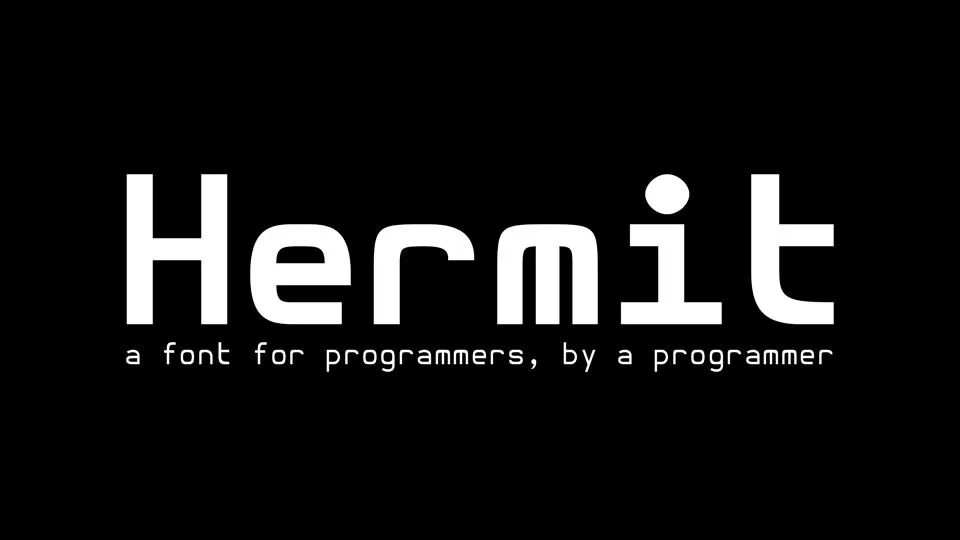
A fonte Hermit é uma família de tipo geometricamente simples desenvolvida para ser clara, prática e extremamente legível. Suas linhas são diretas e retas, criando um visual minimalista que se destaca perfeitamente em ambientes digitais modernos. Combinada com seu foco nas práticas do desenvolvimento de software, a Hermit é uma escolha perfeita para designers gráficos, especialmente aqueles dedicados ao design web ou programação. A atenção aos detalhes na criação da fonte garante que cada letra seja calculada e planejada segundo preceitos bem definidos, resultando em um conjunto de caracteres consistente e regular. Ideal tanto para títulos quanto para textos mais longos, a Hermit se sobressai como uma opção de tipo sem serif perfeita para projetos digitais atuais.